Seit heute präsentiert das ZDF seine Nachrichten aus einem neuen, virtuellen Studio. Mit 3-D-Modellen, Animationen und einem präzisen Design möchte der Sender seine Erklärkompetenz stärker herausstellen. Für die Zuschauer sollen Zusammenhänge besser und verständlicher dargestellt werden. Dabei darf die Nachrichtenvermittlung im virtuellen Raum nicht an Glaubwürdigkeit verlieren.
Das Zentrum in dem 700 Quadratmeter großen pastellgrünen Studio bildet die aus drei Flügeln bestehende Moderationsinsel aus Nussbaumholz, Acrylglas und Kunstleder. An dieser präsentieren die ZDF-Moderatoren im Stehen. Sie präsentieren die Nachrichten nicht mehr vom festen Standort des Moderationspultes, sondern gehen – im doppelten Sinne – auf den Zuschauer zu.
Eine technische Besonderheit sind zwei Kameraroboter, die sich automatisch im Raum bewegen. Sie garantieren präzise und identisch wiederkehrende Kamerafahrten, eine wesentliche Voraussetzung für die Regie des neuen Erscheinungsbildes.
Die Schrift für die Einblendtexte, Icons und das Infografikkonzept sollen aus dem Hause EdenSpiekermann stammen, wie über Twitter zu erfahren ist. Nicht nur deren Premiere war überzeugend: Das heute-journal hat durch die Bank überrascht und Maßstäbe gesetzt. Ein Bilderbogen:
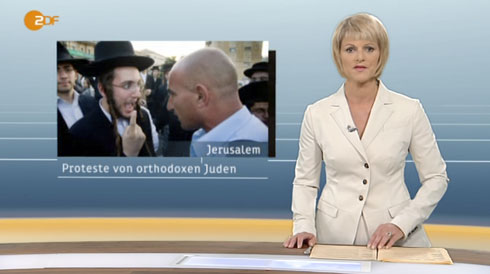
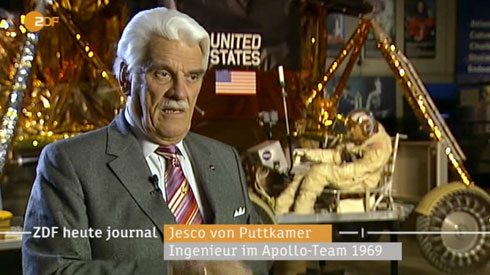
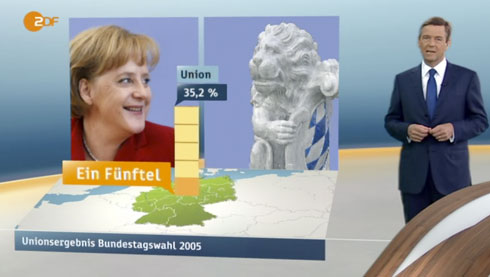
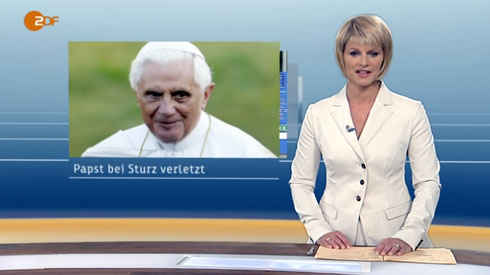
den moderationstresen fand ich etwas heftig vorallem in der totalen sieht er mir zu sehr nach raumschiff enterprise aus aber im großen und ganzen ein sehr gelungener auftritt.
farblich passt es gut, sieht nach zdf aus und wirkt nicht zu aufdringlich. der font ist super lesbar und hat einen eigenen charakter was die infografiken nochmals unterstreichen. teilweise vielleicht etwas zuviel effekte die nicht sein müssen und etwas ablenken, aber vielleicht gibt sich das ja noch wenn sie die ersten rentern beschweren ;)
jetzt noch das heute/zdf-logo verbessern und alles passt.
Ein bisschen seltsam finde ich die Weltkarte im Hintergrund. Mal davon abgesehen dass dort ein kompletter Kontinent unter den Tisch fällt finde ich diese Phantasiegrenzen doch sehr irritierend. Zuerst hatte ich ja befürchtet dass dort die gerade behandelte Weltregion hervorgehoben wird (a la „das Orange da ist ist übrigens der Nahe Osten“), doch im ZDF-Chat meinte Theveßen dass das lediglich aus „künstlerischen“ Motiven erfolgte. Sowas läuft dem Sinn einer Karte ja an sich schon zuwieder, und dann auch noch in einer Nachrichtensendung?
Diesmal nutzen Sie den Platz, dass durch das 16:9-Format entsteht, viel besser.
Das Layout finde ich grundsätzlich gut, vielleicht ein bisschen zu blass und pastellfarben. Was aber wirklich nervt und stark von der Kernkompetenz (nämlich den Nachrichten und Informationen) ablenkt, sind die ganzen Animationen und Bewegungen. Überall zischt irgendwas im Hintergrund herum, hechten die Moderatoren durch die Gegend, wird herein- und herausgezoomt. Das trägt überhaupt gar nichts zur Vermittlung von Informationen bei, wirkt nur hektisch, kindisch und verspielt. Und das sage ich als Unter-dreißig-Jähriger…
Schick! Nur mit der Form des J komme ich nicht klar. Kann man die Schrift irgendwo größer bewundern?
Bin auch begeistert von der Ästhetik und dem Raum. Die Bildbeiträge sind fast schon einen Tick zu technisch und verspielt. Da braucht es noch eine klare Linie. Aber was solls, ist ja nur Fernsehen.
Modern und stilvoll ist es, ja. Aber wirkt das Ganze nicht mittlerweile zu steril und unnatürlich? Ich finde, der Moderator als Person geht in diesem höchst-digitalen Studio völlig unter. Gerade das hat mich bis dato an den Fernseh-Nachrichten noch immer so überzeugt: Die Menschennähe und die persönliche Note. Das kann meiner Meinung nach nicht durch die modernste Technik kompensiert werden. Im Gegenteil.
Oh ha. Das ZDF macht sich auf und versucht sich zu verjüngen (her mit den 14- bis 29-Jährigen). Der Versuch ist allein nicht strafbar und gerade für ein etabliertes Format sehr mutig. Man vergleiche die sehr dezenten Veränderungen bei der ARD / Tagesschau. Letztere bleib ich treu. Dem Inhalt wegen, aber auch der für mich näheren Präsentation.
Mal sehen :-)
pastellgrün?
Die “Aktuelle Kamera” lebt also wieder. Trotz netter Details insgesamt alles sehr verspielt.
Die Schrift würde ich mir auch gern genauer anschauen… sie wirkt für mich zu sehr nach Schreibmaschine (vielleicht eine Anspielung zu den alten Nachrichtentickern vergangener Zeiten). Ansonsten gelungenes neues Konzept auch wenn es teilweise zu gut gemeint ist. Es huschen zu viele „Nachrichtensignale“/„Informationen“ im Hintergrund; aber wenigstens in die richtige Richtung. Insgesamt den Privaten weit voraus.
Vielleicht könnte Erik noch etwas zur Schrift sagen. Auf der Agenturseite bzw. seinem Blog ist nichts zu finden.
Ein Blick ins ZDF-Forum spricht Bände. http://www.zdf.de/ZDFforum/ZDFheute/inhalt/19/0,3672,7605267,00/
Wetterkarte: Die Darstellung der Windstaerke mit den neuen Windpfeilen ist unmoeglich. Als Wassersportler an der Kueste braucht es genauere Angaben, so wie es auf jeder metereologischen Wetterkarte Standard ist: Richtungspfeile mit anhaengenden Faehnchen fuer die Windstaerke in Beaufort.